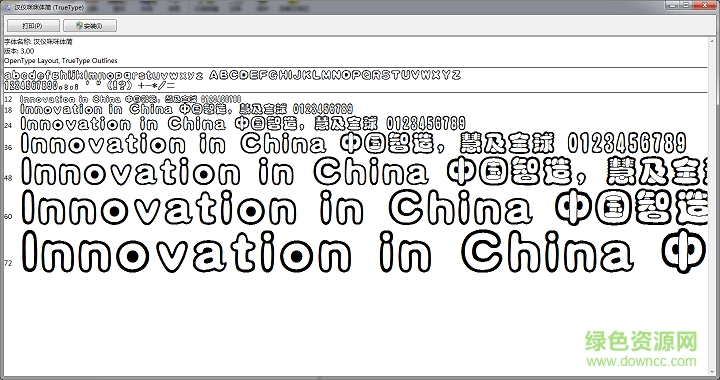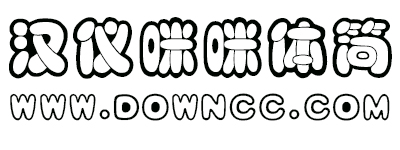
漢儀咪咪體簡(jiǎn)字體
漢儀咪咪體簡(jiǎn)屬于卡通字體。這款字體字如其名,具備貓咪字體特點(diǎn)。字體外形為空心,但是很起來(lái)非常靈動(dòng)!可以用于制作兒童畫報(bào)。喜歡的用戶歡迎來(lái)綠色資源網(wǎng)下載。
漢儀咪咪體簡(jiǎn)字體介紹
漢儀咪咪體簡(jiǎn)是一款空心的,并且邊緣筆畫較粗的簡(jiǎn)體字體,整個(gè)字形比較圓潤(rùn),還是很可愛(ài)的,用于制作賀卡、明信片是不錯(cuò)的選擇。
漢儀咪咪體簡(jiǎn)